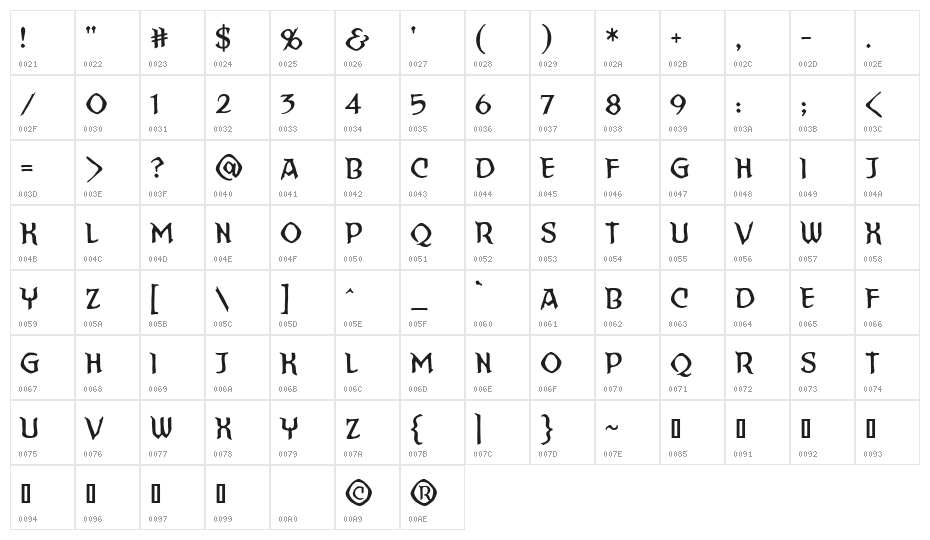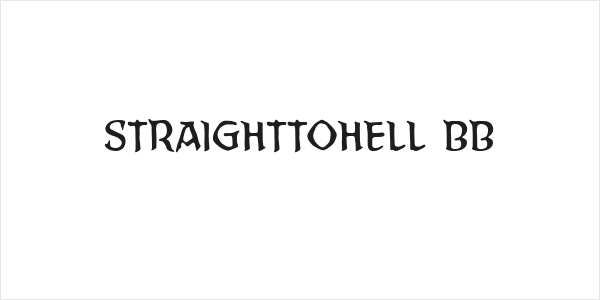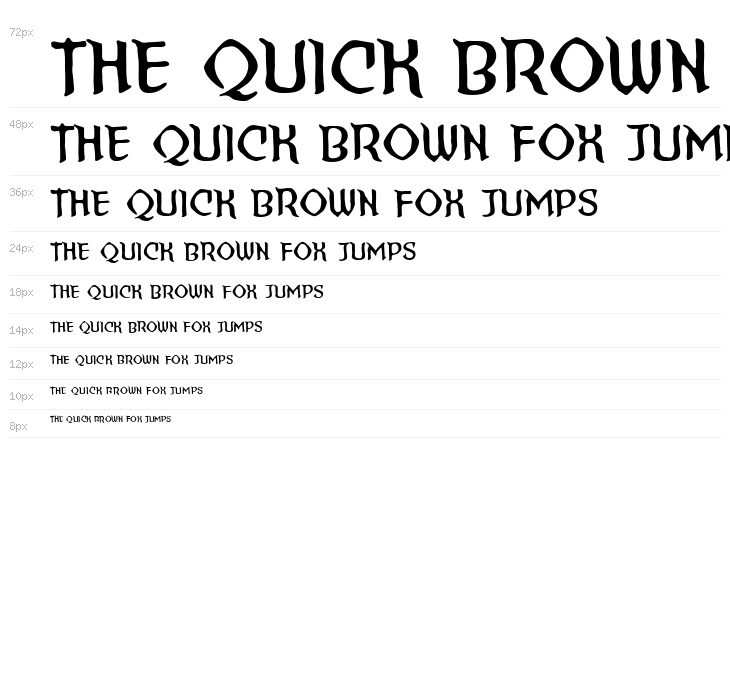
StraightToHell BB Font
✎ Gothic
| Kategorien | Gothic |
| Gesamtstil | Gothic, Dramatic |
| Vorgeschlagene Projekte | Ideal for use in horror-themed designs, album covers, posters, and branding that requires a bold, edgy look. |